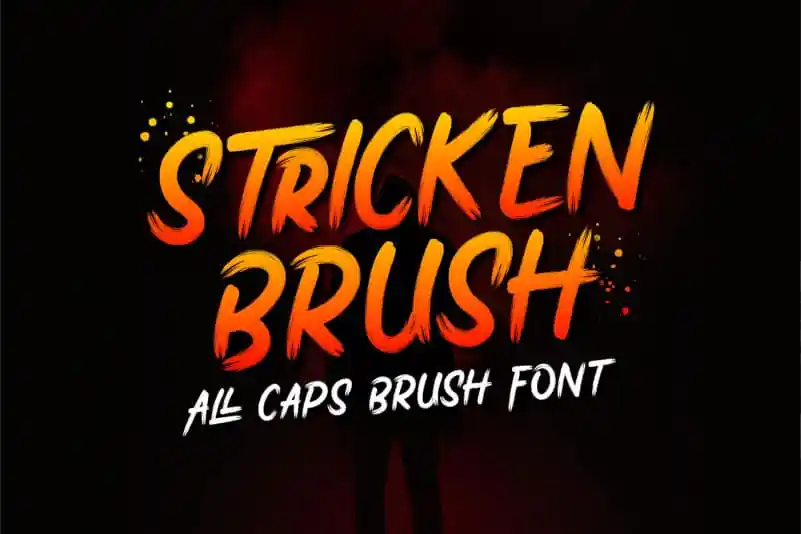
Stricken Brush Font – Download Grátis
A fonte “Stricken Brush Font” é uma combinação perfeita de elegância e originalidade. Ela transmite um sentimento suave e amigável, com traços fluidos que lembram uma autêntica escrita a lápis. Seu design original mantém o brilho de uma fonte à mão enquanto oferece uma presença atenciosa em qualquer projeto gráfico. Especialmente adequada para aplicar um toque especial às suas criações, esta fonte é ideal para aqueles que valorizam estilo e charme no seu trabalho final. Neste caso da categoria Brush Fonts, ela é apresentada pelo designer famoso nurfdesigns.
Designer: nurfdesigns